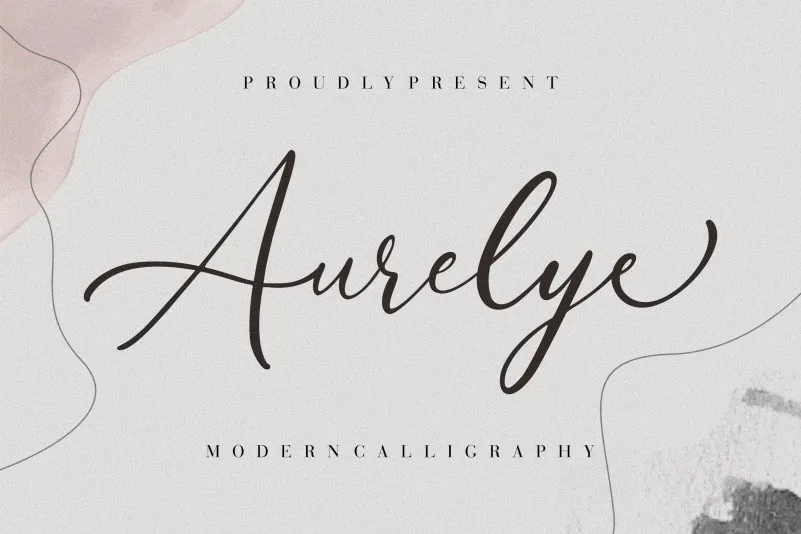
Aurelye Calligraphy Font é uma elegante tipografia criada pela Creatype Studio com traços fluidos e delicados que remetem à arte da escrita aquarelada. Seus detalhes delicadamente elaborados, combinados com o uso de alternativas estilizadas e ligaturas, oferecem um toque único e sofisticado para qualquer projeto visual. Este script font é perfeito para quem busca uma textura suave e uma atmosfera acolhedora em suas criações digitais. Com Aurelye Calligraphy Font na sua coleção de fontes, você adicionará profundidade e elegância à sua tipografia sem comprometer a legibilidade. Sem dúvida, ela será um excelente complemento para qualquer design gráfico que valorize textos alegres e artísticos.